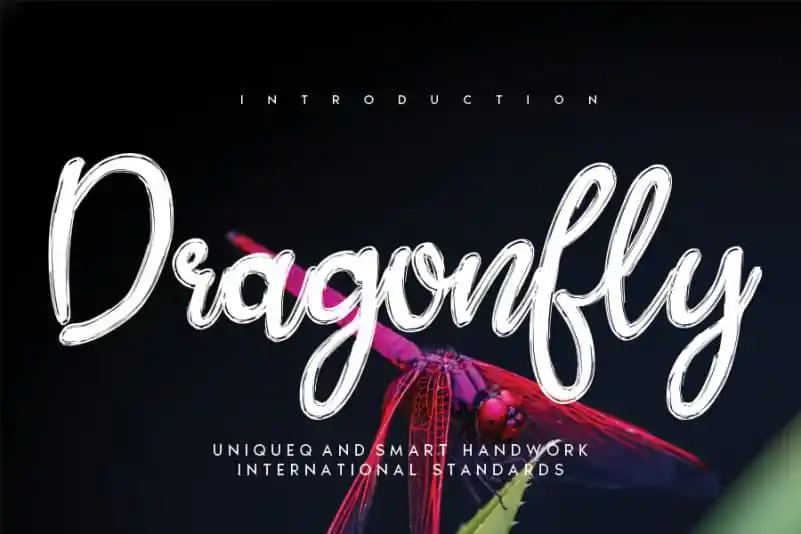
A Dragonfly Brush Font é uma escolha perfeita para quem busca uma fonte que transmite frescura e casualidade ao mesmo tempo. Ela é perfeitamente adaptada para criações digitais como a carregada de personalidade das postagens no Instagram, bem como para texturas elegantes utilizadas em projetos DIY. Seja você um designer profissional ou iniciante, esta font pode transformar seu texto em verdadeiros trabalhos de arte. Com uma atmosfera amigável que faz qualquer ideia criativa parecer única e especial, a Dragonfly Brush Font é uma ótima adição para designers gráficos. Suas linhas levementes mas fortes garantem que sua marca seja memorável e profissional, enquanto seu estilo casual mantém-a acessível e envolvente. Nesta categoria de Script Fonts, a Dragonfly Brush Font é um dos recursos indispensáveis para qualquer designer em busca de uma font que não apenas ajuda a transmitir suas ideias de maneira mais criativa, mas também os torna verdadeiras obras de arte.